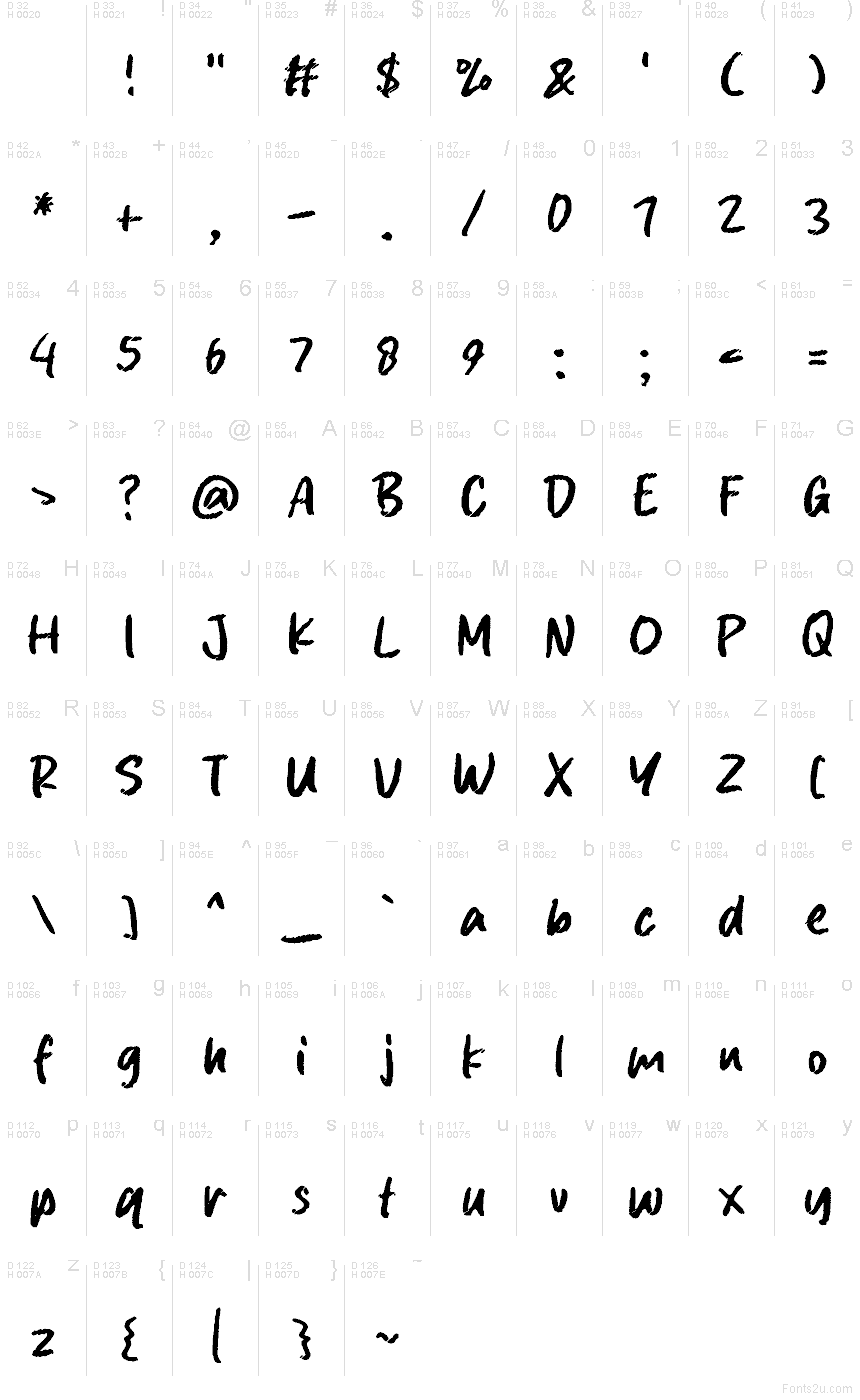
Rainy Calm, par Origin Type, est une police manuscrite gratuite au style pinceau, dotée d'un rythme fluide et de formes peintes à la main. Ses traits larges, ses bords irréguliers et la variation de pression donnent aux lettres un aspect spontané de peinture à l'enseigne, tandis que les jonctions imparfaites conservent un caractère authentique plutôt que trop lisse.
Utilisez cette police gratuite pour l'identité visuelle de cafés, des affiches d'événements, des pochettes d'albums, le packaging de produits et des titres courts qui ont besoin d'une touche humaine. Le mouvement énergique du pinceau trouve toute sa place dans les textes courts, tandis que sa texture irrégulière confère une atmosphère informelle et expressive.